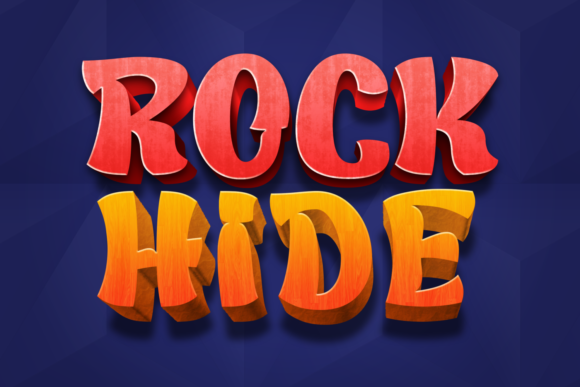
Rock Hide Font
Rock Hide Font – خط عصري وجريء لمشاريعك الإبداعية
Rock Hide Font هو خط فريد يجمع بين الأسلوب العصري والطابع القوي، مما يجعله الخيار المثالي للمصممين وصناع المحتوى الذين يبحثون عن لمسة جريئة ومتميزة. يتميز الخط بحواف حادة وتصميم ديناميكي يناسب مجموعة واسعة من الاستخدامات، بما في ذلك الشعارات، العناوين، الملصقات، تصميمات السوشيال ميديا، والتغليف.
مميزات الخط:
✔ تصميم احترافي وعصري
✔ مناسب للمشاريع الطباعية والرقمية
✔ مثالي للعناوين والهوية البصرية المميزة
أضف لمسة إبداعية إلى أعمالك مع Rock Hide Font واجعل تصميماتك تنبض بالحياة!